Myriad AppleとMyriad Proは同じ?
WebDogにてApple製品のロゴのフォントはMyriad(ミリアド) というエントリーが上がっています。
エントリー名にある現在のアップル製品のロゴのフォントはMyriad Proだという結論に違和感を感じたので、改めて調べてみました。
確かに「Myriad Pro Regular」は「Myriad Apple Medium」とほぼ同じ、「Myriad Pro SemiBold」は「Myriad Apple Bold」とほぼ同様のようでした。「Myriad Apple Medium」は「ヒラギノ角ゴシック W3」に、「Myriad Apple Bold」は「ヒラギノ角ゴシック W6」にあわせて、少し文字サイズを大きくしているような記憶があったのですが勘違いでした。
ただ、Myriad Appleの方は、shift+opion+Kでアップルロゴ、shift+option+pで小さいアップルロゴが割り当てられているなど、アップル関連の文書では依然、こちらが使われていることが予想されます。
もうひとつおさえておくべきポイントとして、小塚ゴシックではその従属欧文にMyriadを採用しているという点です。ただし、こちらは和文とのバランスを考え、文字サイズが大きめに設定してあります。
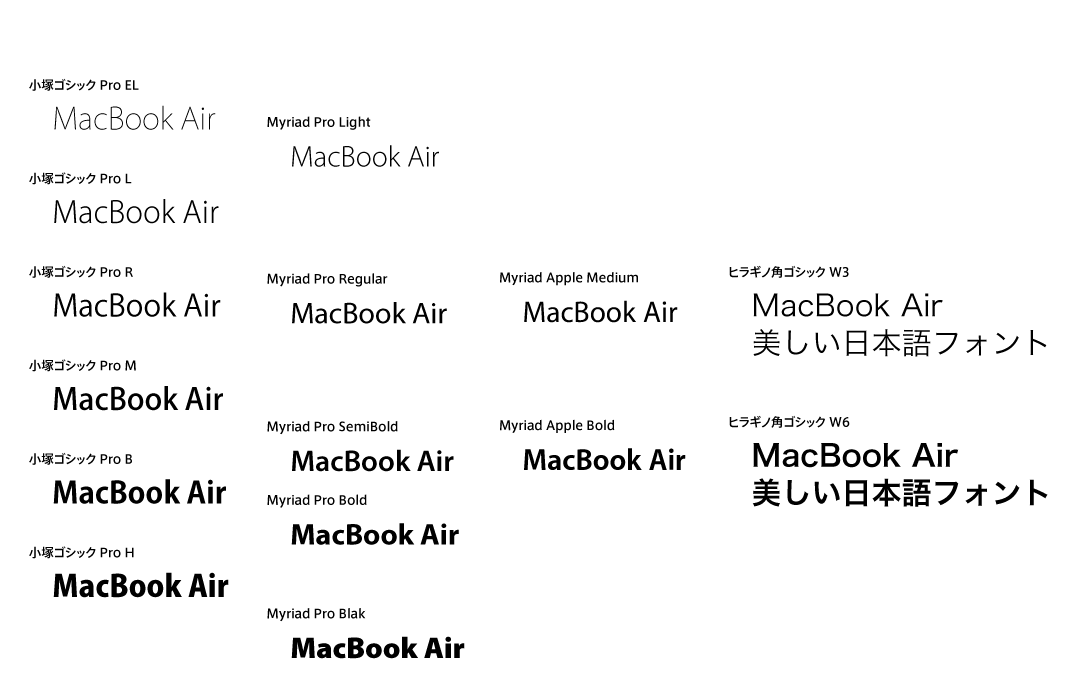
Myriadといえば、その昔「Multiple Master」というウエイトや文字幅を自在に変更できるフォントとしてリリースされたような覚えがあります。
16年くらい前に、アドビ製品で使われているこのフォントなんだろう?と探し回って、Font Too.で購入しました。今でも飽きがこない美しいタイプフェイスです。